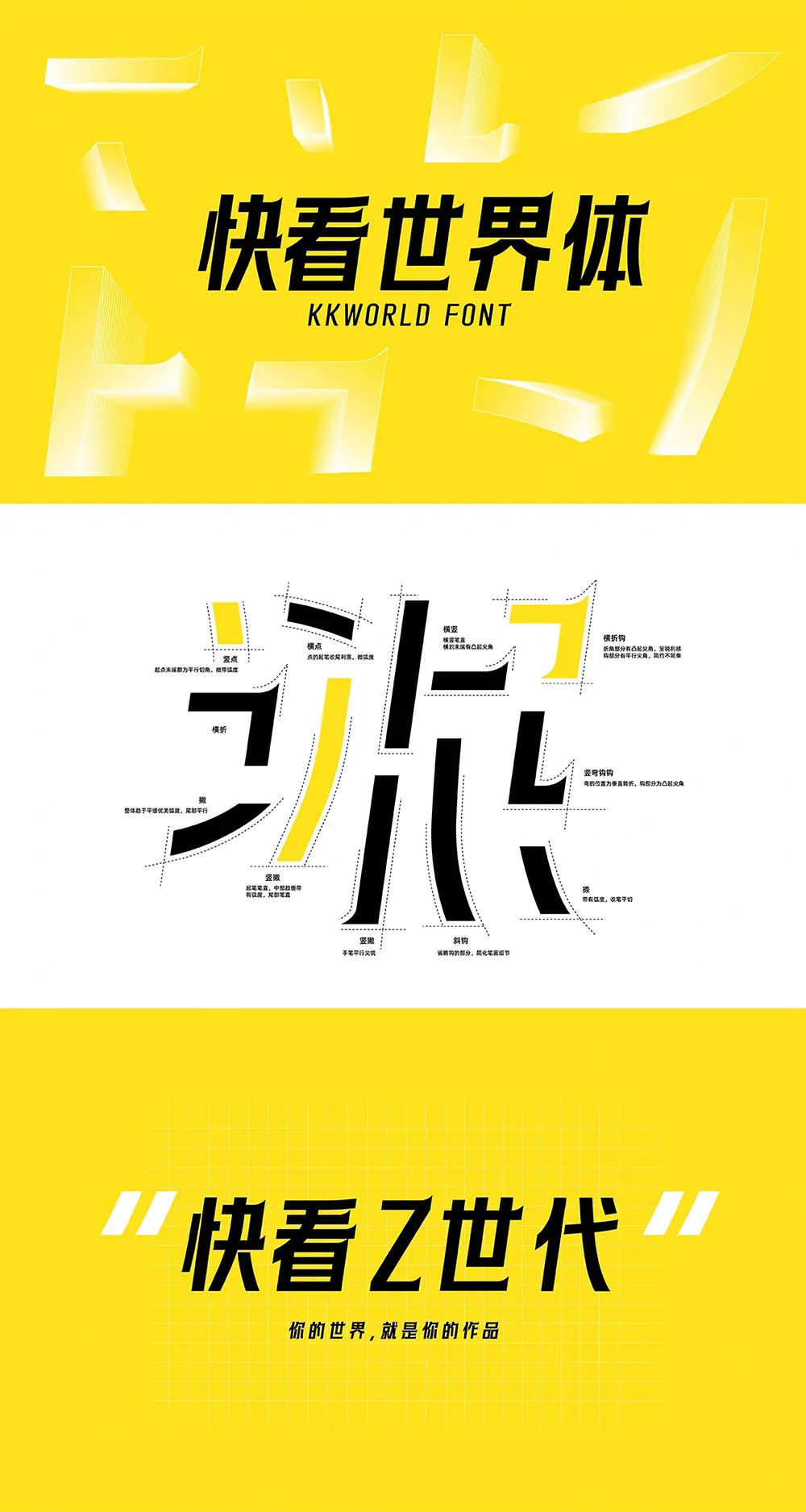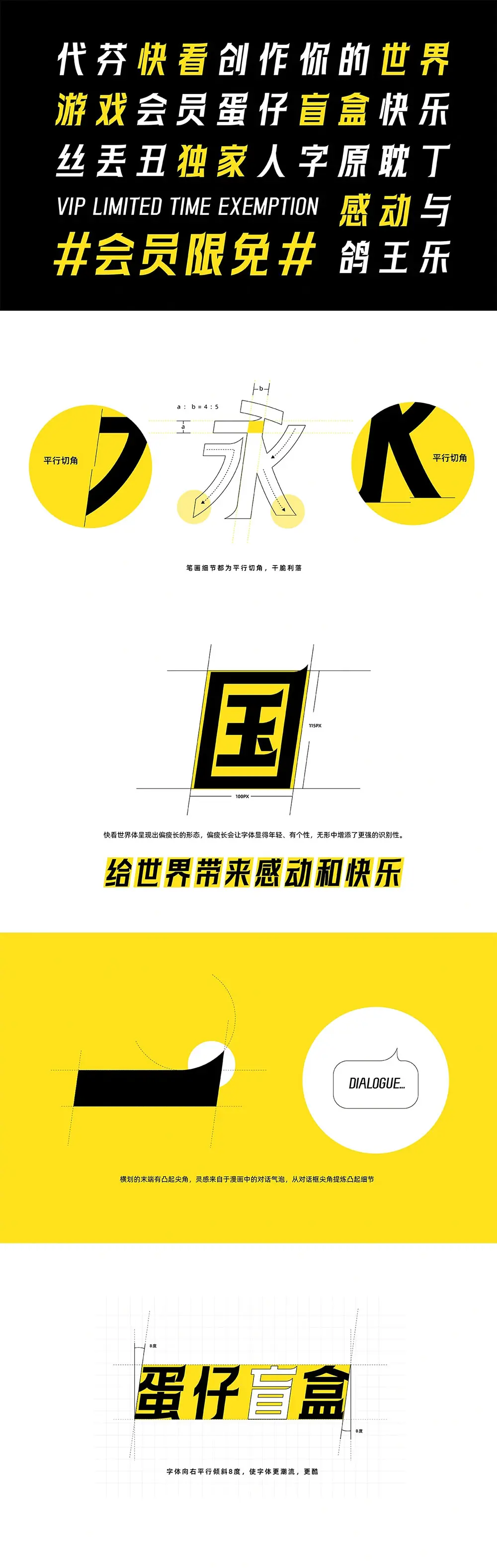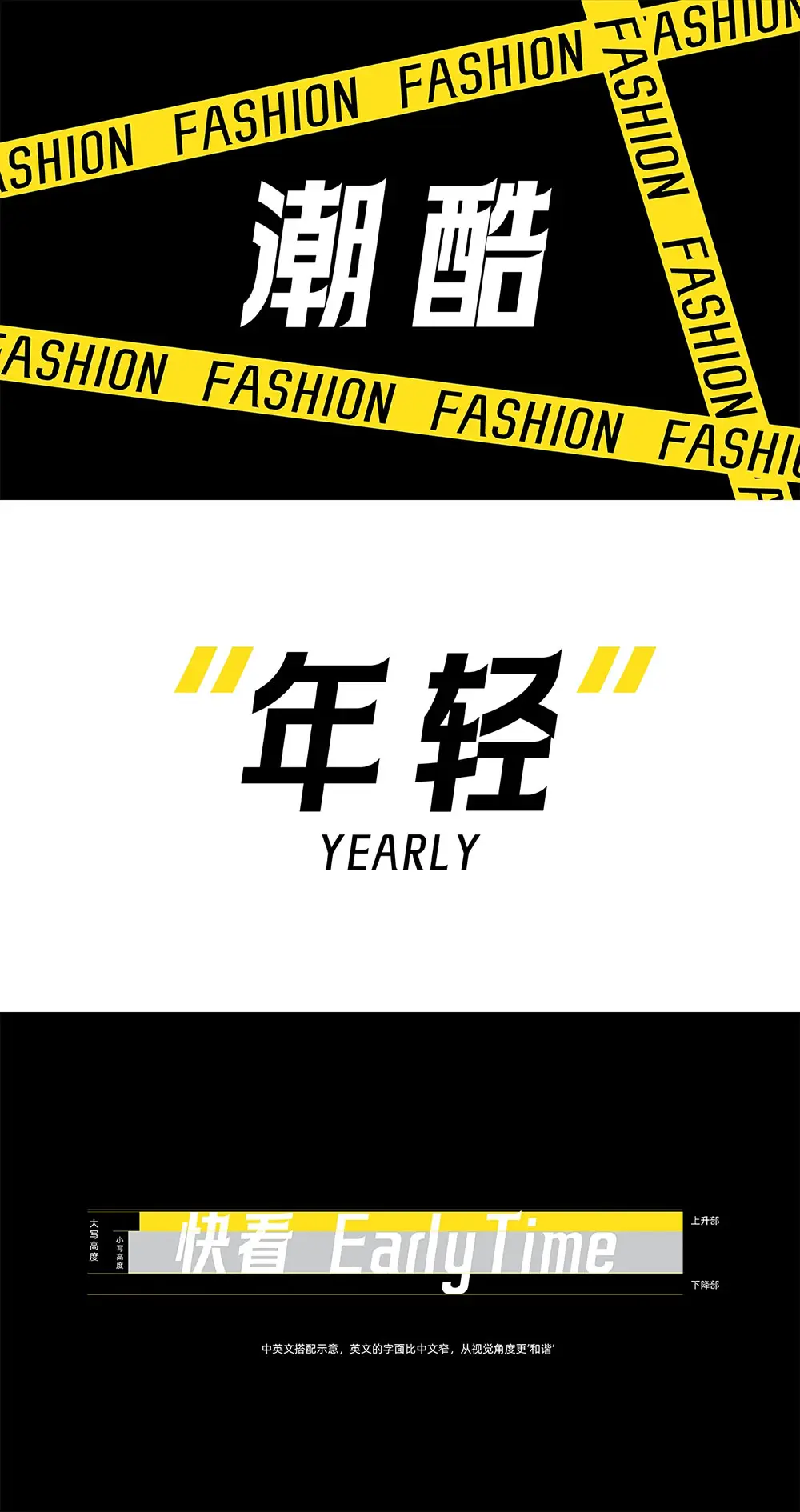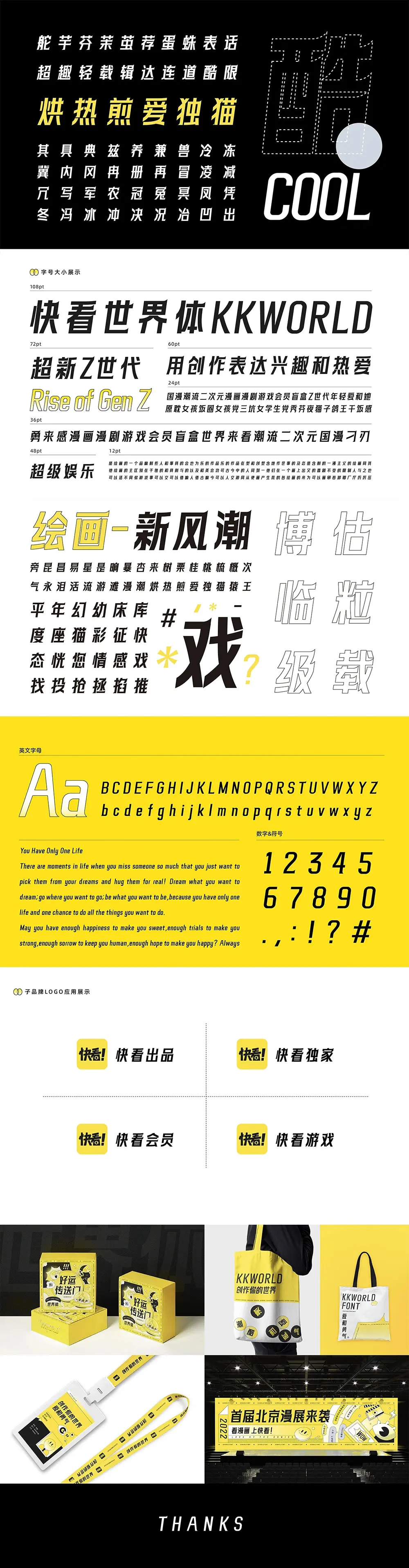
快看世界體介紹
這款字是我第一款從設計-封裝-測試全部自己完成的字庫快看世界體由快看KKDC出品,字體設計以漫畫中的對話框元素為起點,融入快看ACGN文化,年輕潮流,大膽有態度。
字體特點末端尖角,中宮外擴、字面瘦長、傾斜8度;包含3501個字。現應用於快看品牌營銷、漫展、內部企業文化宣傳、客戶端等場景。免費授權全社會使用(包括商用)